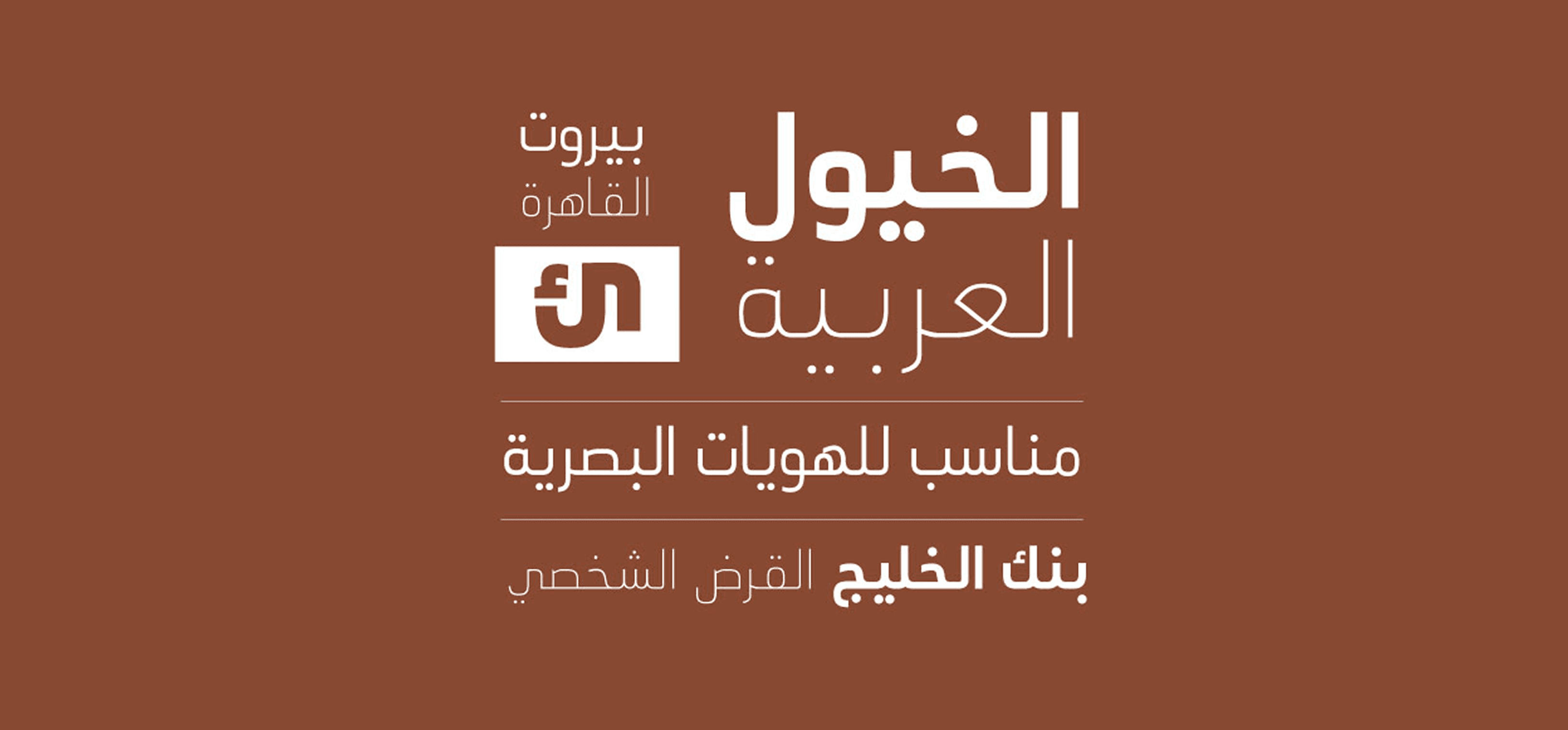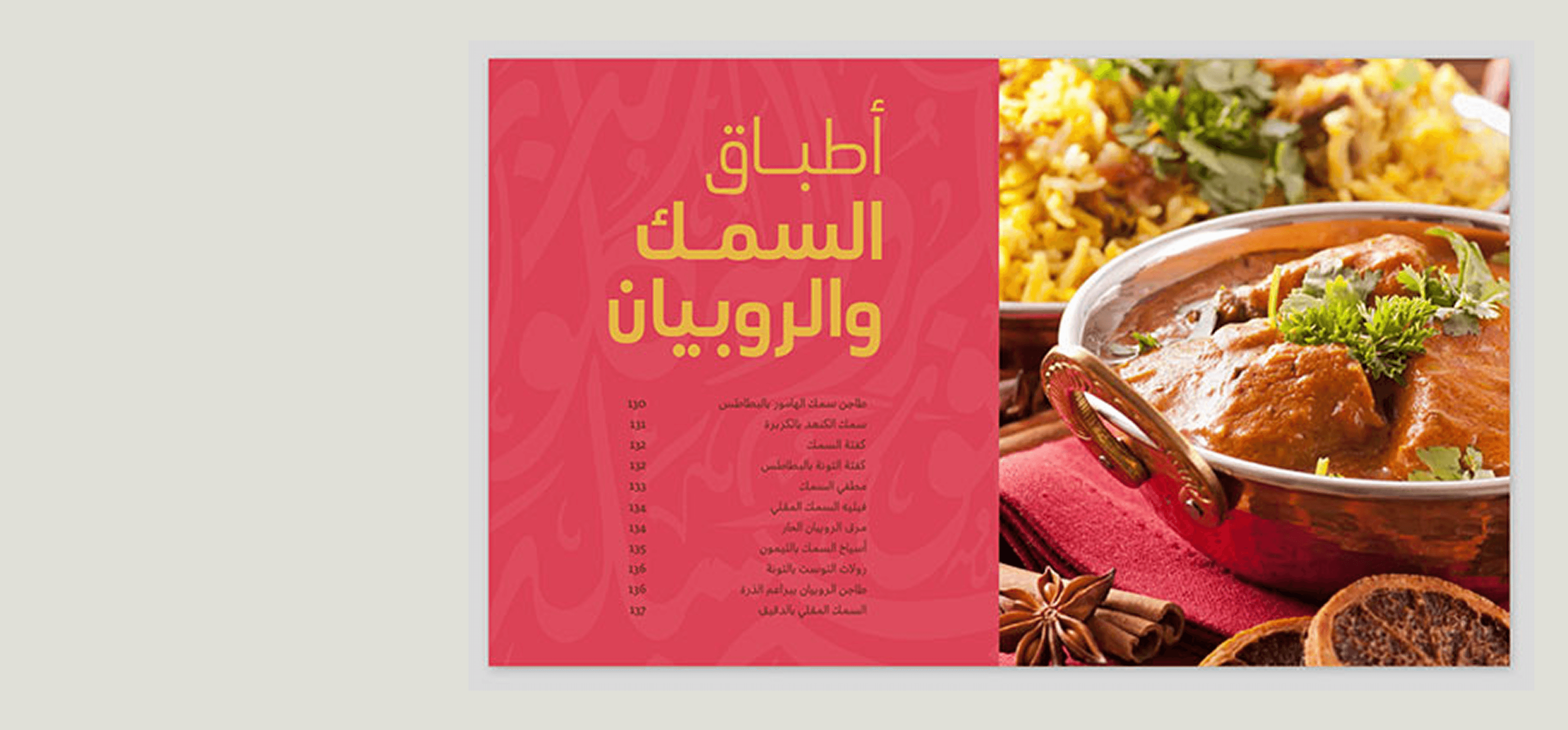
الخط العربي المعاصر هو فونت عربي طباعي يتألف من أربعة أوزان: لايت، عادي، بولد و اكسترا بولد مما يعطي خيار واسع في طريقة استعماله. تم تصميمه ليكون بحلة عصرية تتميز بجمالية الشكل وسهولة القراءة. يسهل استعمال هذا الخط العربي مع الخطوط اللاتينية ال sans serif. الخط العربي المعاصر مناسب للاستعمال في الهويات البصرية وكل التصاميم الغرافيكية خصوصاً العناوين او في المطبوعات المختلفة.